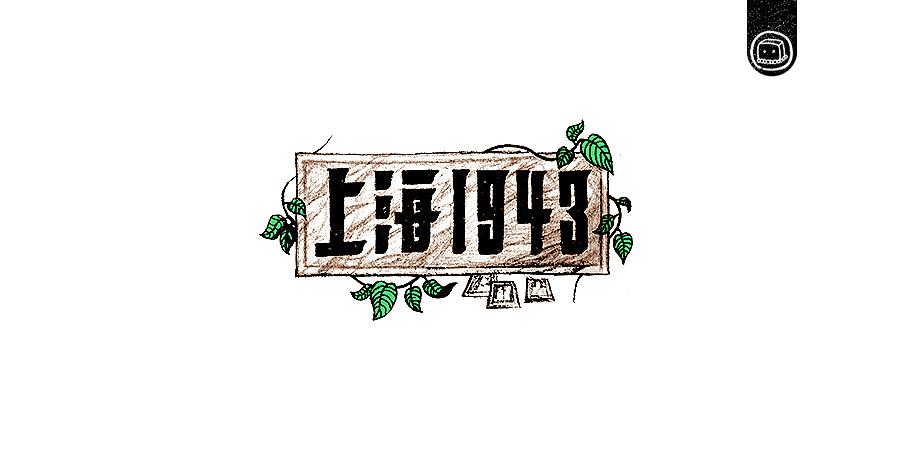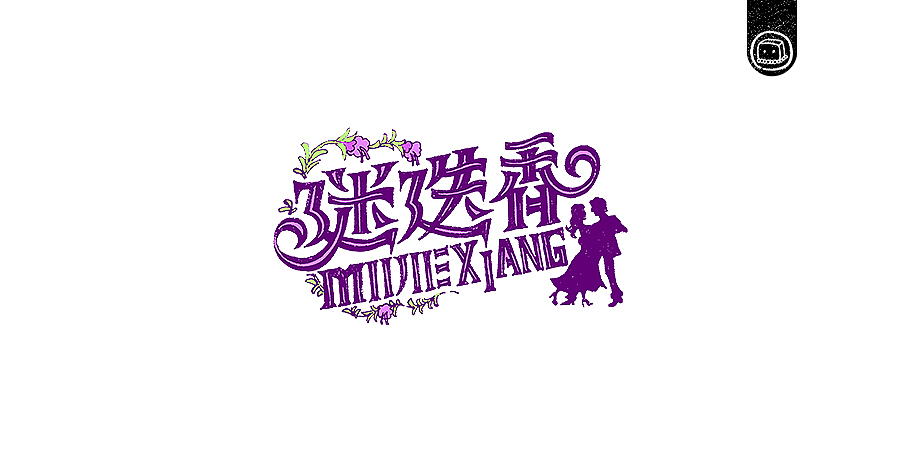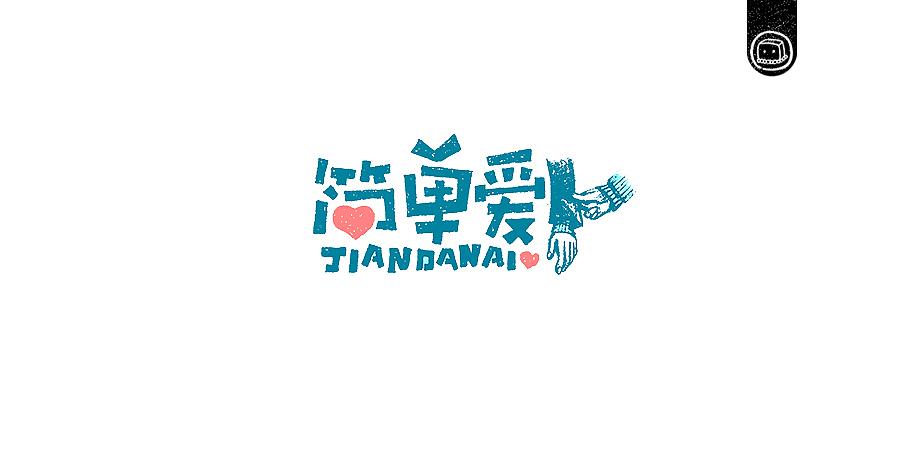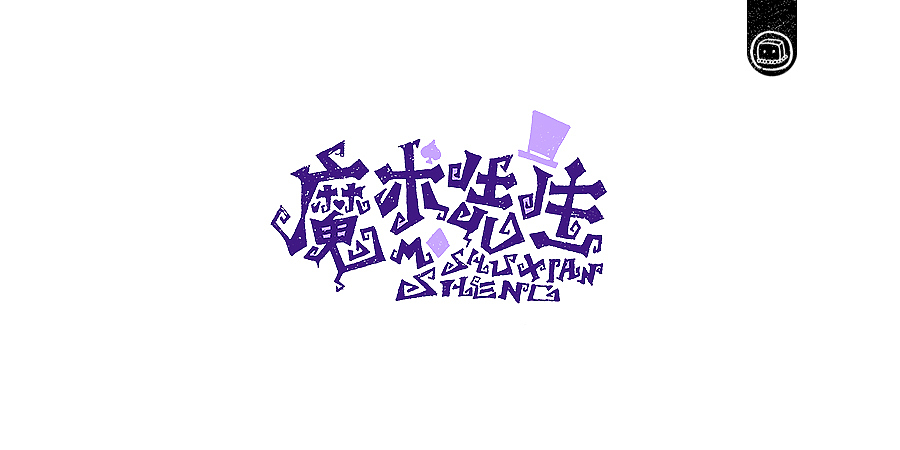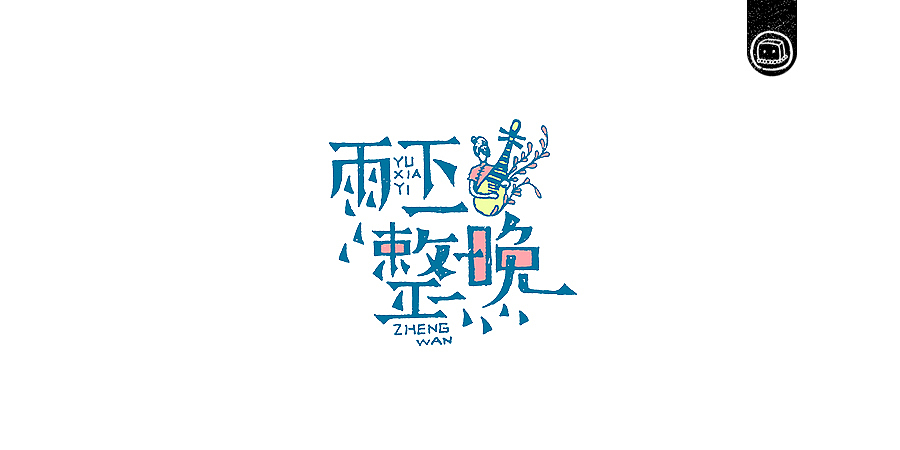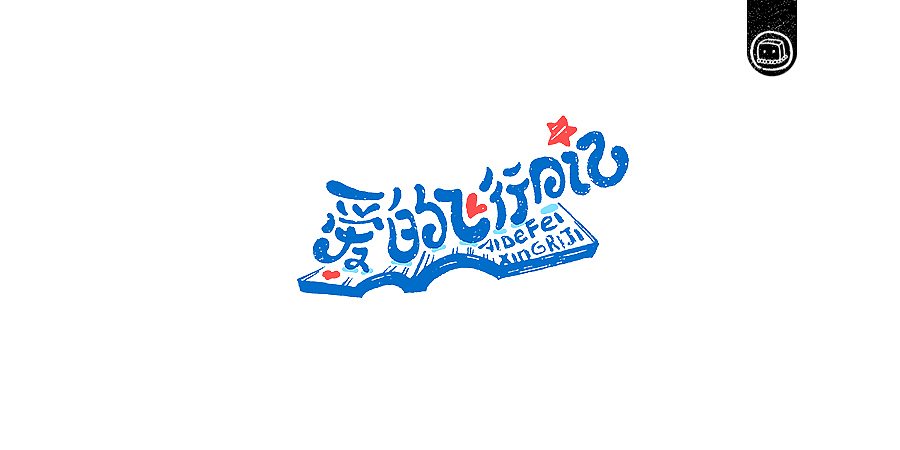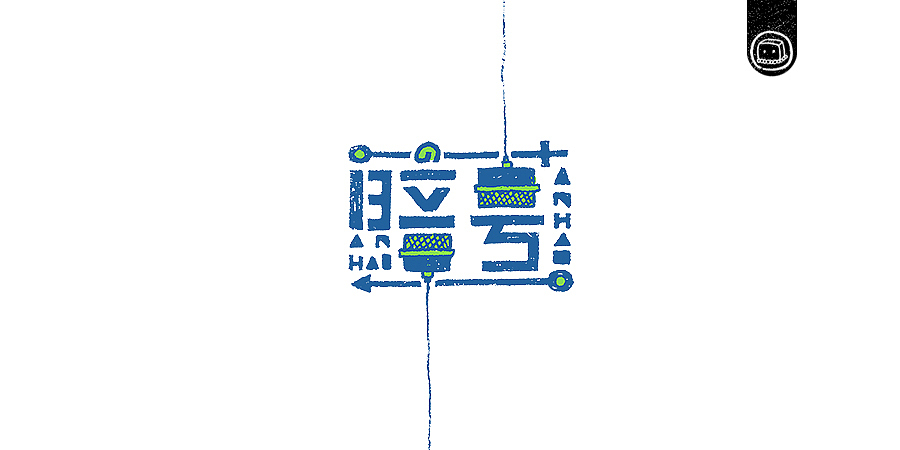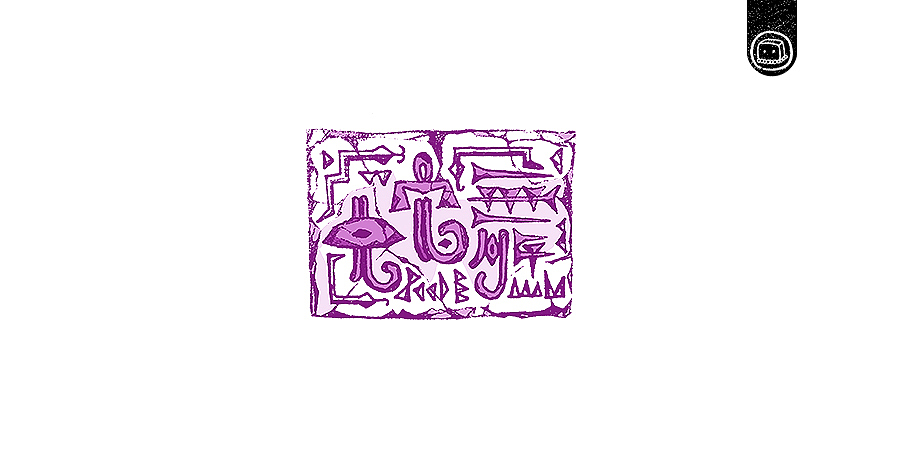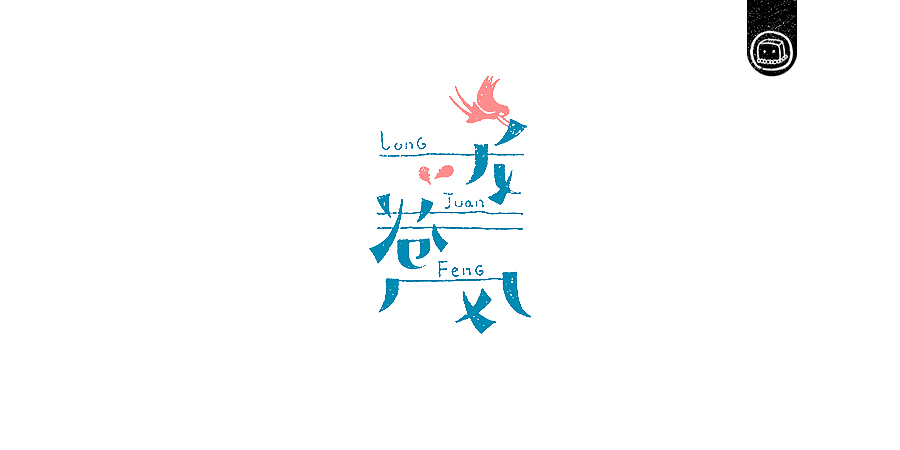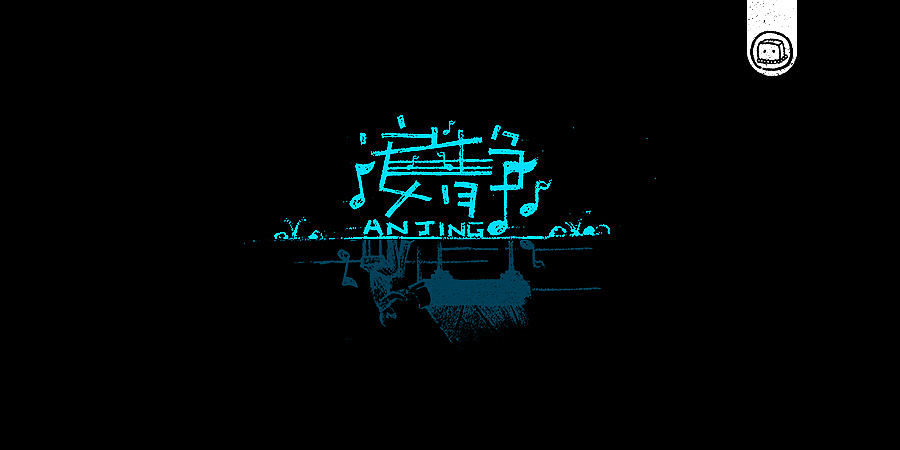
字画字说——《杰伦的那些歌》
继上次的教程我提到的最近的创作《杰伦的那些歌》第一波已经完成,整整三十件作品。整套创作分为三个阶段;第一波30件作品,第二三波都是各35件作品。希望大家能够喜欢和支持,小僧谢过!
为了这次的创作。我这三个周都在听杰伦的歌。以前只是觉得歌好听。没太在意剧情或者写歌的意义。为了这次创作我找了一下资料(其实就是问了度娘)对着每首歌的MV是一遍一遍不停的看。去提炼,去把握打动我的瞬间。希望这次的每一幅画面都能让你走进画中,走进我的“字的世界里”(噗哈哈哈,喂!妖妖灵吗,这里有个和尚在装13)我把没首歌的创作灵感和我对歌曲的理解感受都写出来了。希望有兴趣的可以看看。(写那么多字不容易啊,对于这个语文是历史老师教的来说,很不容易啊!)
灵感来自于《爱的飞行日记》里的一句歌词 “找一颗星 只为了你命名”
对的!那颗星就是我对你的爱!(好害羞)
提取的歌词里面我给“你的爱写在西元前···泥板上的字迹依然清晰可见”
爱超越历史,但是你的那张美丽的脸庞却深深地烙印在我的心中
“只剩下钢琴被我弹了一天”每次听到这句歌词,都能带我到那安静的画面,一条小河边,一架钢琴,流水声,钢琴声,自然之声——是最美的音乐
女性的魅力犹如迷迭香的味道迷人,MV里出镜率最高的莫过周杰伦和女主的舞蹈!
这首歌是周杰伦为电影《不能说的秘密》创作的歌曲,而这个电影的引线就是那本乐谱。一切的秘密,都是因为翻开了这本乐谱!
这首歌的MV,比较悲伤,主角想脱离那些打打杀杀,烦恼的日子。重新平静的的生活。在生活中遇到了普通的她。然而这个MV最打动我的地方就是,结尾女主拖着带病的身体,去给男主买了冰淇淋。当她开心的推开门···却留下了伤心的眼泪(好想哭)
时间的交错,让我遇到了你,又错过了你。
棒棒糖,皇冠,大大的蝴蝶结,再加上撒娇,我累个擦,反正我是受不了
MV里最中意的就是那个从天花板上掉下来的话筒,也许这就是我和你用来沟通暗号的唯一的方法吧。
简单爱,整篇歌词和整片MV里,就像表达“简单”我对你的爱就是想牵着你的手不放开,而且MV最后定格在女主拽着男主的衣袖,而不是牵着手,这让我想到了高中时候的样子;在高中,我想最让男生忘不掉的就是你喜欢的那个人,扯着你的衣袖对你说“我就这样拽着你好吗,就当我拉着你的手”怀念高中的时候,多么的单纯,多么的简单啊···
这首歌写得是,对自己爱的人就不要放弃,爱他/她就永远不要拿着借口去伤害她/他,把借口装进瓶子里,让它消失在大海,永远不要打开。
“我就是开不了口,让她知道···”这个想到了我的以前,有过心动的女孩纸,每次经过她家门前虽然看不到她趴在窗口(这种画面只有电影电视里会有吧)但还是会抬头看一眼(噗哈哈哈)
让龙卷风带走你的爱吧,既然不能在一块儿,就大胆的放开手,让龙卷风传达给你最后的答案吧
魔术先生吗,不用多说,玩的就是魔术,玩儿就是不一样,周杰伦的这首歌融合了很多曲风,甚至把《牛仔很忙》的格调融进了里面。整首曲子就像一个魔术师在变魔术一样
一个小铁匠,为了一把吉他,努力的工作,虽然苦虽然累,在MV里,那个画面——他终于买到了自己梦寐以求的吉他,很认真的在弹着吉他的样子,很让人替他开心。如果你有梦想的话,就努力的去实现他吧。坚持!你一定会有收获!如果没有收获,那是你坚持的程度还不够!
“窗外的麻雀,在电线杆上多嘴···”七里香给我的永远都是很惬意,温馨,甜蜜的画面。有吉他的美妙声音,有麻雀的叽喳声,有七里香的香味。想想整个画面···如果再有个她——怎一个浪漫可言
字如其歌,双刀,给你,踏上你的战场,开始你的战斗吧!
蛇舞,给我的感觉就是神秘,埃及的文明我一直非常喜欢,就借着这首歌,把自己的喜好融进去了。神秘感,历史感。就在你的眼前
“一件黑色毛衣,两个人的回忆···”噗哈哈哈,想到了高中时候,我女朋友给我织的围巾了(莫名的在傻笑,让我再去笑一会儿)
这首歌是周杰伦为百事可乐创作的歌曲,要有自己的性格,让大家跟“我”同一种调调!
看到这个,你有没有看到雪碧logo的既视感,没错,这首歌就是为雪碧组织的篮球竞赛创作而来,想到篮球,让我想到了当年的那个红毛小子不屈不挠的篮球热血!没错,就是樱木花道!
说走就走,带上吉他,带上乌克丽丽,带上美女(哦,美女被约走了,不在了)要的就是这种随意,开心就好。说干咱就干!想那么多干嘛!
《自导自演》的创作,就是因为周杰伦喜欢雪铁龙的这款GT!其实我也喜欢,可惜买不起,我就看看吧!
《晴天》记录的是学生时代,那种单纯,可爱的恋爱。MV,最打动我的就是杰伦翻墙,去找心仪的她的那个桥段,我想到了我在学生时代,也干过这样的事儿,确实很学生(噗哈哈哈)不知道你们有木有这个经历
这首歌不搜不知道,一搜原来如此。我最开始以为这首歌是干嘛的,问里度娘,看了MV才知道,这就是一种冰淇淋,土耳其冰淇淋就是这种玩儿的,“玩儿弄”顾客之后,才给到顾客去吃。最开心的就是那个挑逗的过程,有趣好玩儿有意思。就是这首歌曲想表达的意思
《黑色幽默》是一种表现手法,矛盾,夸张,神经的等。鱼缸颠倒水却撒不出来,鱼儿离了水,却在自由的游来游去,用黑色幽默的表现手法来表达了,不能在一起的残酷和悲伤。
泛黄的照片,老字体,黄金葛。种种元素道出的是对老上海时候的战争,拆散的亲人的一种想念!
犹抱琵琶半遮面,忧伤的中国风。没有雨伞的雨夜,感觉好凄凉啊
这首歌很励志!却又看破红场,就像歌词写的“这第一名到底有多强”从想得到第一名,到最后放弃第一名,我就在想,得了第一名又能如何呢?你依然是三年二班的那个你,不是吗?
本来听到歌名以为是写的很惬意,谁知道啊,谁知道,写的是两个好基友,同时喜欢上一个女孩纸,然而都不好意思去表白···那你们就互相的折磨吧,反正那个女孩纸不知道你们对她的爱。这首歌告诉我们,爱她就大胆的说出来吧!
这个我换了个黑色的背景,安静的夜!感觉也不错!